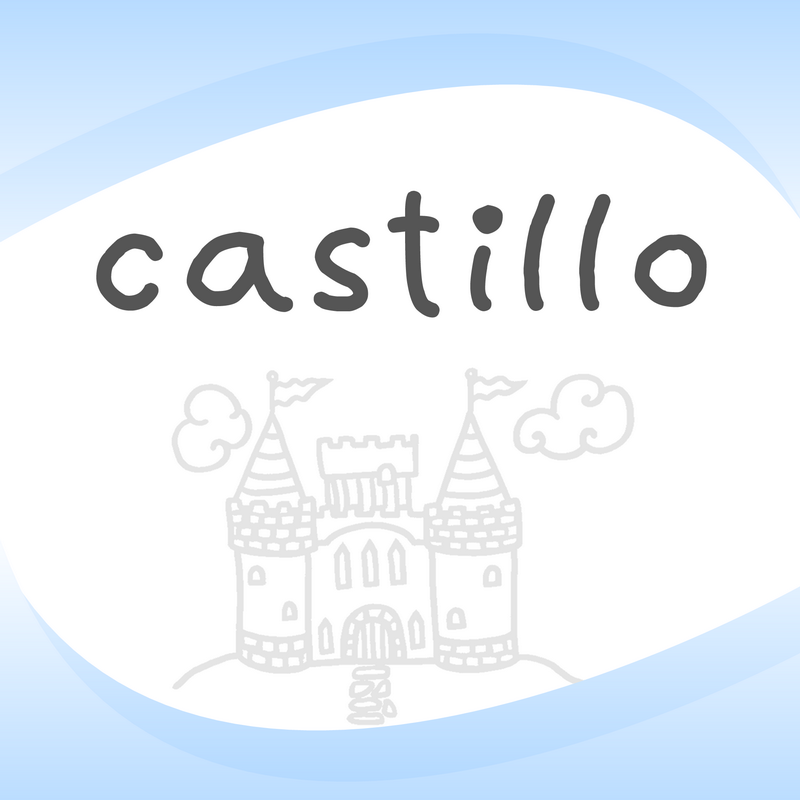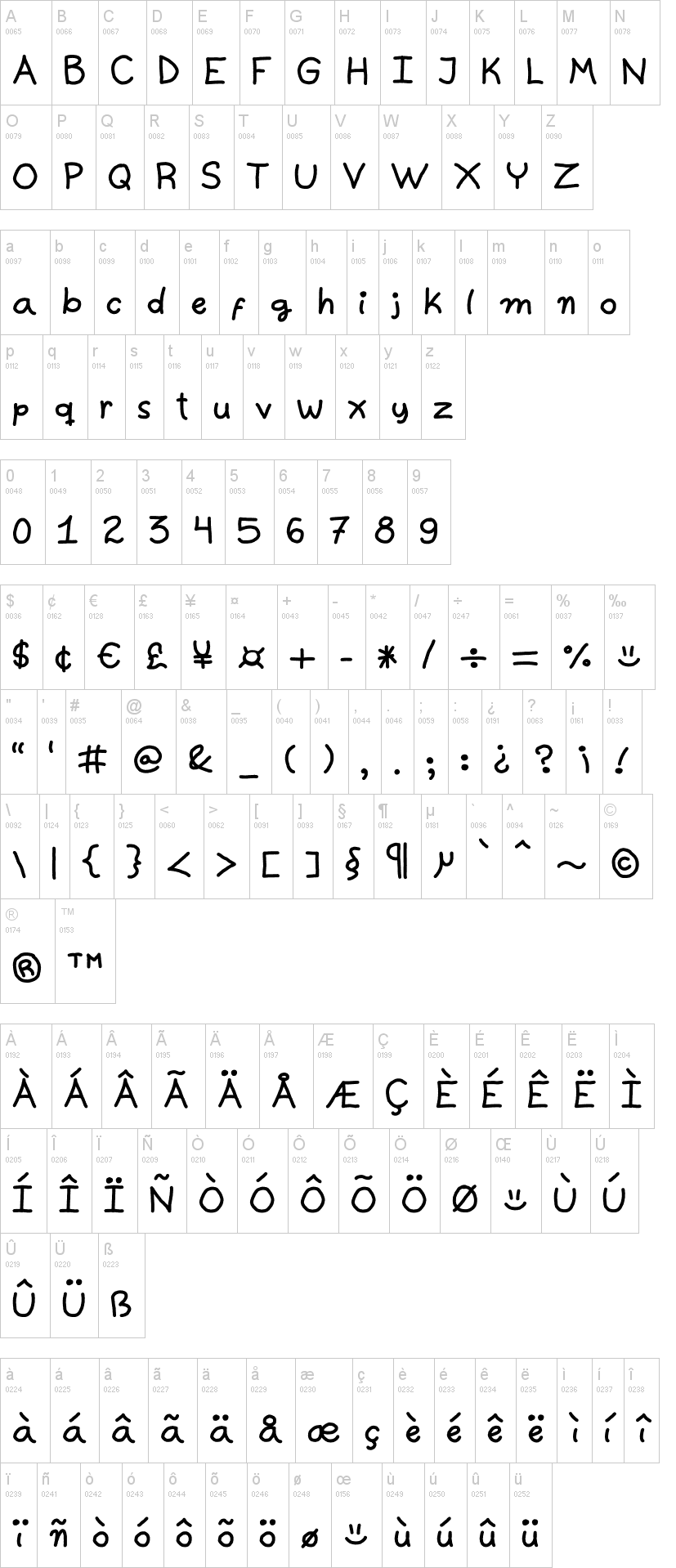
Tipografía hecha a mano, llamada "castillo" incluye acentos, signos de interrogación y exclamación iniciales, entre otros. Espero que te guste. Acepto donaciones vía PayPal.